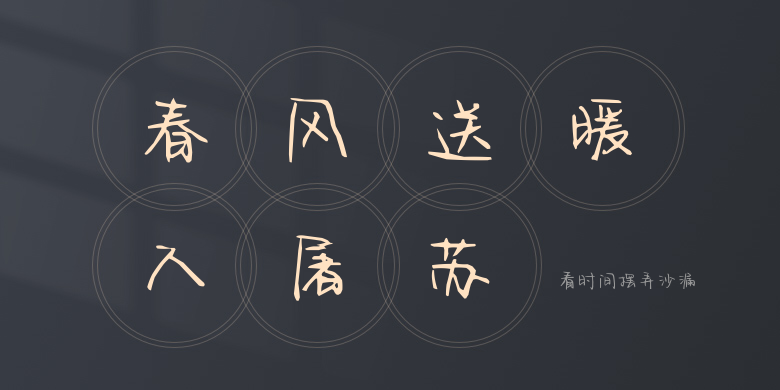
看时间摆弄沙漏
看时间摆弄沙漏,这款字体结构工整、笔画清晰,兼顾美观与易读性,适用于标题、正文、海报、包装、LOGO 等多种场景。字形优雅稳定,风格百搭耐看,适配日常排版与创意设计,让文字呈现更舒适、更具质感。看时间摆弄沙漏一笔一画,皆是细节,以均衡的比例、流畅的线条打造舒适视觉体验,字形端正大气,风格简约现代。无论是商业设计、品牌宣传还是日常排版,都能轻松驾驭,让文字更有格调与力量。看时间摆弄沙漏字体下载。